Font chữ ký Việt hóa đang trở thành lựa chọn không thể thiếu trong các thiết kế cần sự tinh tế và cá nhân hóa. Tuy nhiên, nhiều người gặp khó khăn khi tìm font đẹp, dễ đọc và đặc biệt là hỗ trợ đầy đủ tiếng Việt mà không lỗi dấu.
Việc sử dụng font không phù hợp có thể khiến thiết kế thiếu chuyên nghiệp và giảm giá trị thương hiệu. Trong bài viết này, In Viva sẽ cung cấp 20+ font chữ ký Việt hóa đẹp, được sử dụng nhiều nhất, giúp bạn dễ dàng lựa chọn và nâng tầm mọi thiết kế.
Tải 20+ font chữ ký Việt hóa phổ biến hiện nay
Phông chữ ký Việt hóa là lựa chọn lý tưởng cho những thiết kế cần sự tinh tế, cá tính và dấu ấn riêng. Với đặc trưng mô phỏng chữ viết tay tự nhiên, các font này mang đến cảm giác mềm mại, uyển chuyển nhưng vẫn hiện đại, giúp tổng thể thiết kế trở nên nổi bật và chuyên nghiệp hơn.
Nhờ khả năng hỗ trợ tiếng Việt đầy đủ, phông chữ ký Việt hóa có thể ứng dụng linh hoạt trong nhiều lĩnh vực như logo thương hiệu, thiệp cưới, chữ ký email, poster, bao bì sản phẩm hay các ấn phẩm nghệ thuật mang tính cá nhân hóa cao.
Font Việt hóa Manchester Signature
Font Việt hóa Manchester Signature sở hữu phong cách viết tay thanh lịch với các nét bút uốn lượn mềm mại, tự nhiên. Tổng thể font mang đến cảm giác sang trọng và tinh tế, rất phù hợp khi sử dụng trong thiết kế logo thương hiệu, thiệp cưới, danh thiếp hoặc bao bì cao cấp. Đây là lựa chọn lý tưởng cho những thiết kế cần sự nhẹ nhàng nhưng vẫn nổi bật.
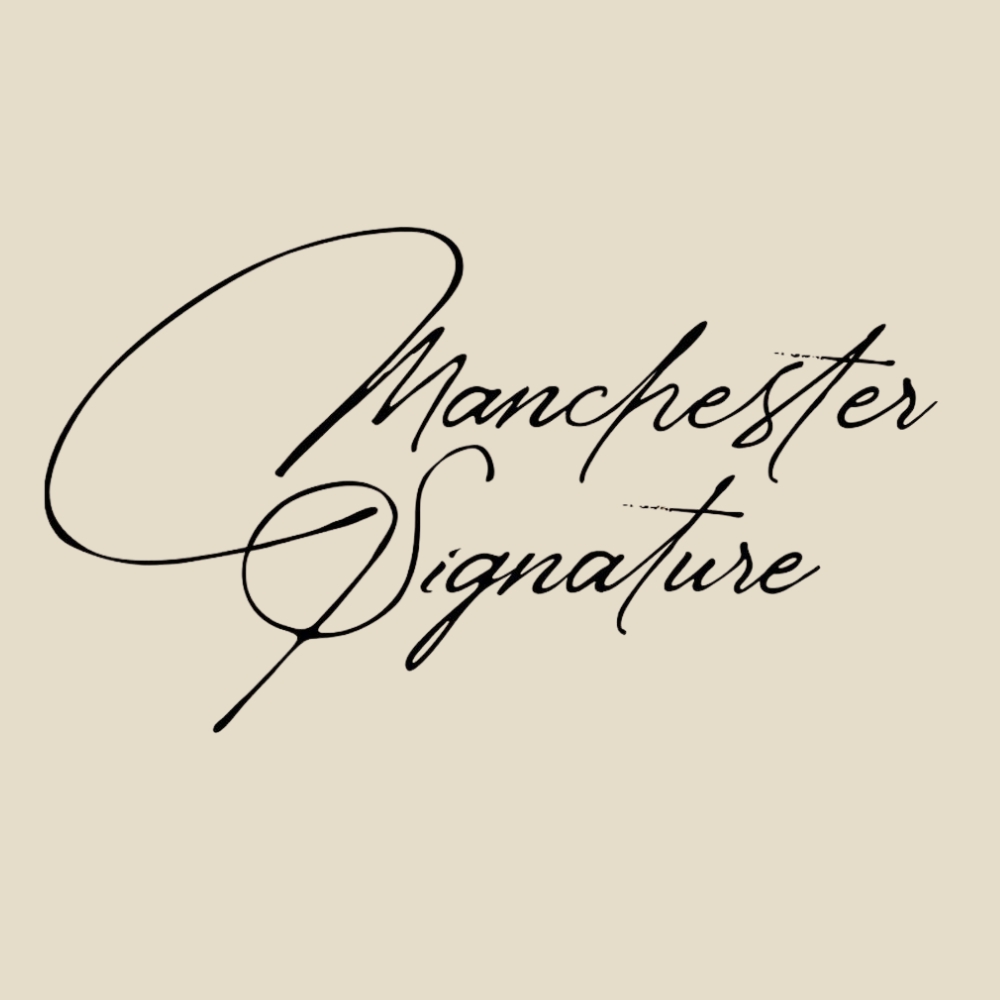
Font Việt hóa Wellyon
Font Việt hóa Wellyon mang phong cách hiện đại với các nét chữ bay bổng, mềm mại và có độ tự nhiên cao như chữ viết tay thật. Font vừa đảm bảo tính thẩm mỹ, vừa dễ đọc, phù hợp với các thiết kế logo cá nhân, thiệp mời, chữ ký email hoặc các sản phẩm sáng tạo mang tính nghệ thuật.
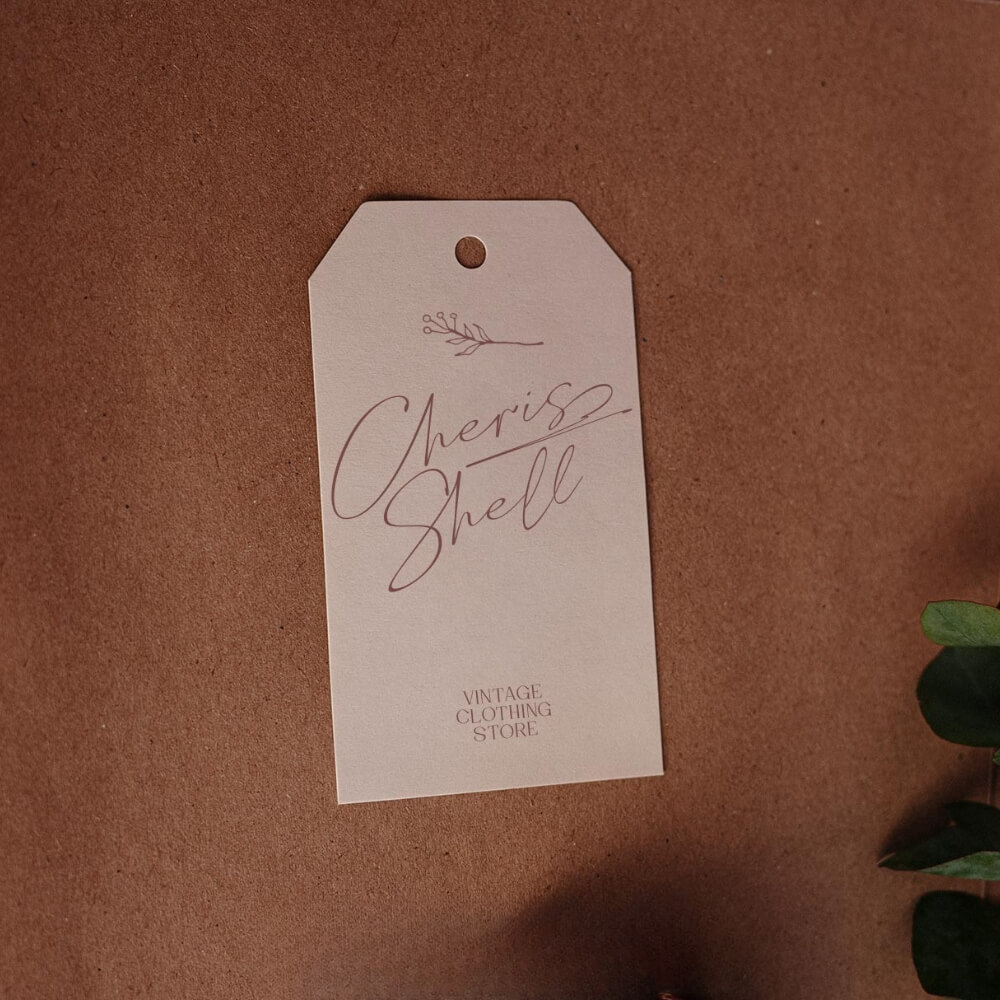
Font Việt hóa Omaha Beach
Font Việt hóa Omaha Beach nổi bật với phong cách mạnh mẽ, phóng khoáng. Các nét chữ dày, uốn lượn rõ ràng giúp tạo điểm nhấn thị giác tốt, rất thích hợp cho poster, banner, logo thời trang hoặc các thiết kế cần sự cá tính và ấn tượng mạnh.
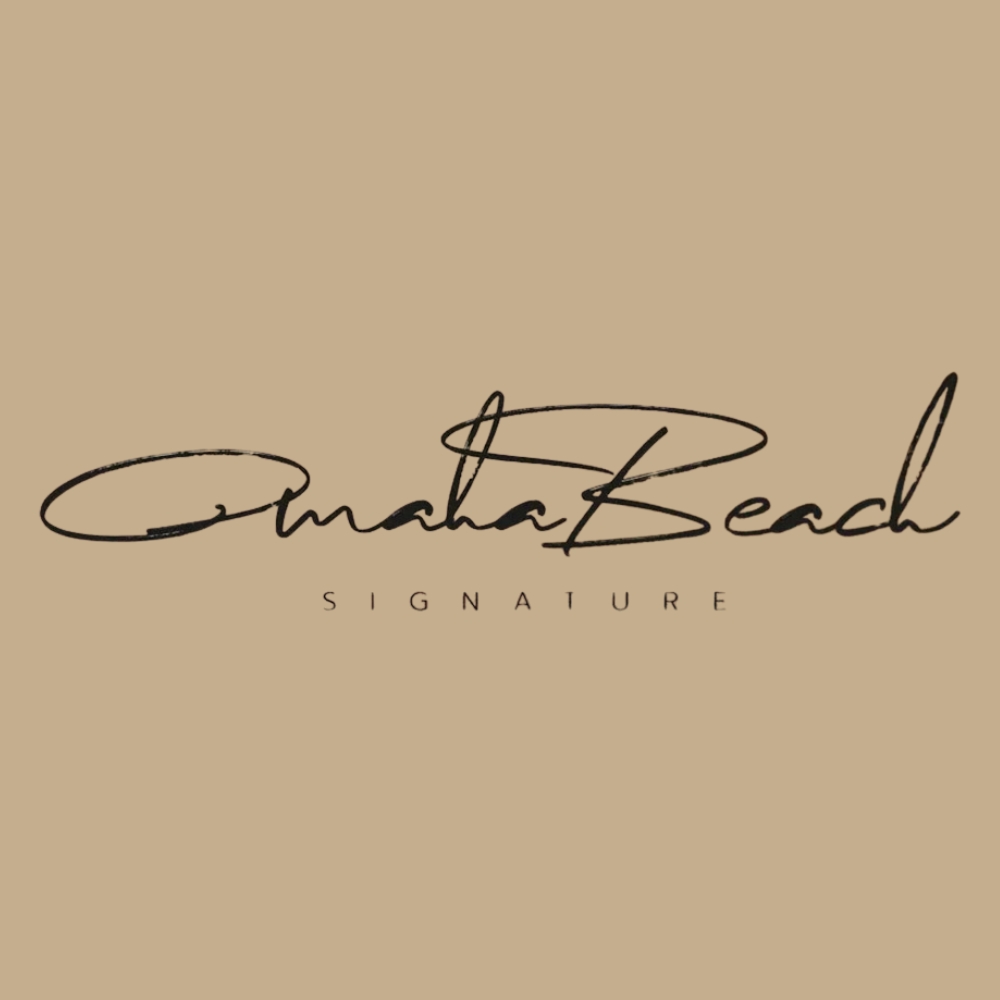
Font Việt hóa Frenchasette
Font Việt hóa Frenchasette có nét chữ thanh mảnh, mềm mại và giàu cảm xúc. Phong cách nhẹ nhàng, tinh tế giúp font trở thành lựa chọn phù hợp cho thiệp mời, logo cá nhân, thiết kế thời trang hoặc các ấn phẩm nghệ thuật cao cấp.
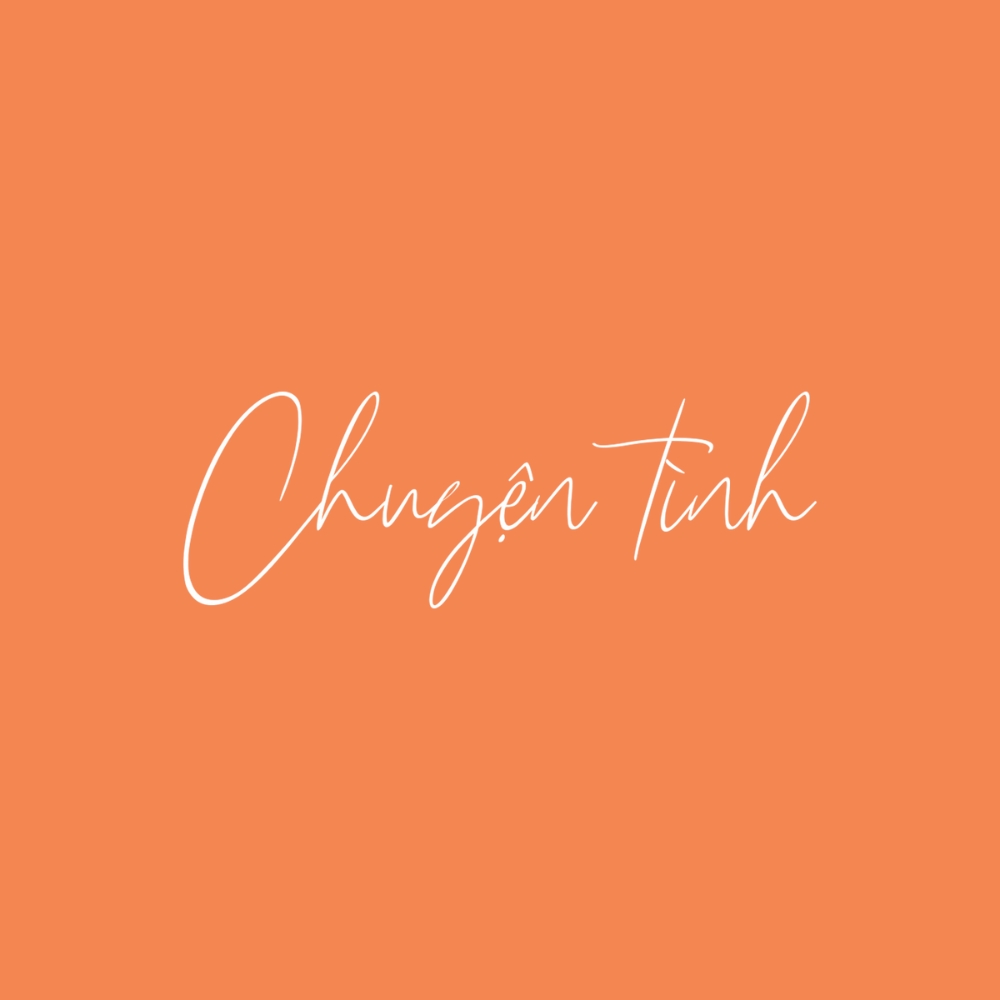
Font Việt hóa TQ Kingston
Font Việt hóa TQ Kingston mang phong cách hiện đại, uyển chuyển với độ cân đối cao. Font giúp thiết kế trở nên tinh tế và chuyên nghiệp hơn, thường được sử dụng trong logo thương hiệu, tiêu đề poster hoặc chữ ký cá nhân.
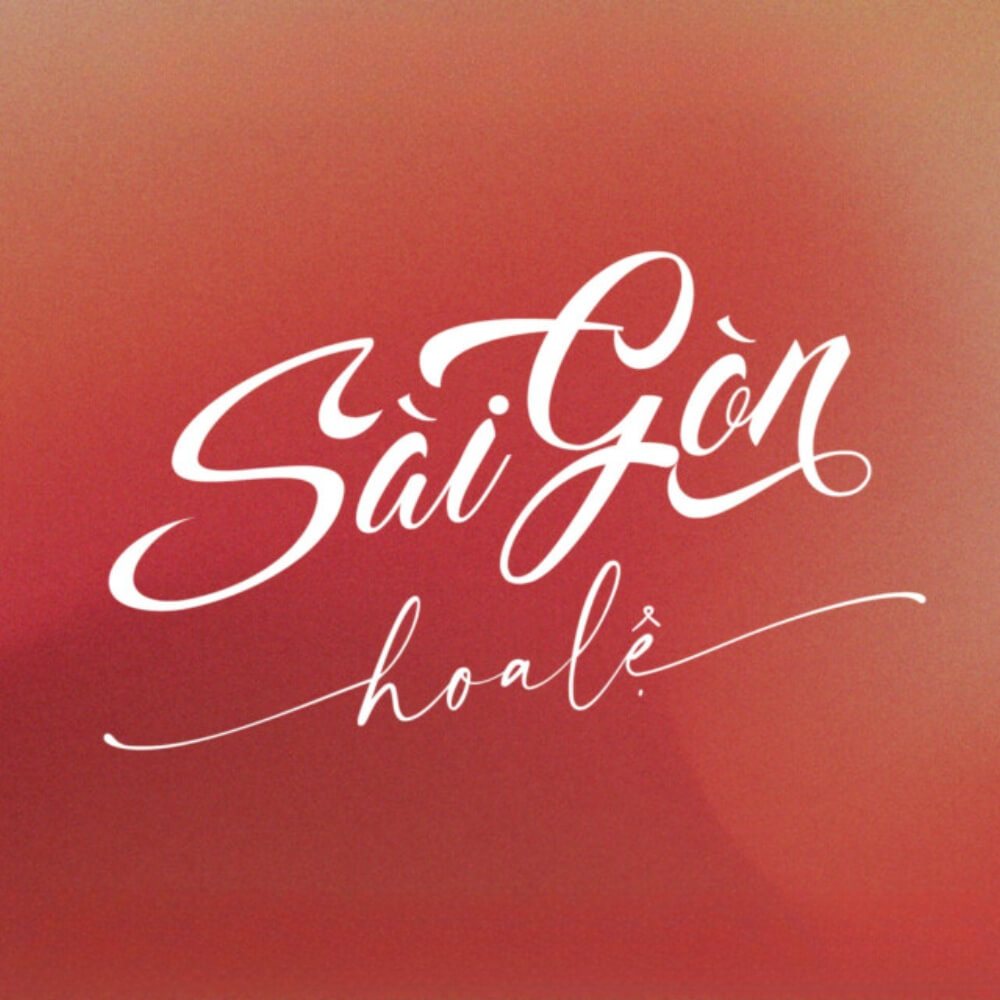
Font Việt hóa SVN Hamstring
Font Việt hóa SVN Hamstring sở hữu các nét chữ mềm mại, bay bổng, tạo cảm giác thanh thoát và nhẹ nhàng. Font phù hợp với các thiết kế thiệp cưới, logo, bao bì sản phẩm hoặc những dự án mang phong cách lãng mạn, tinh tế.
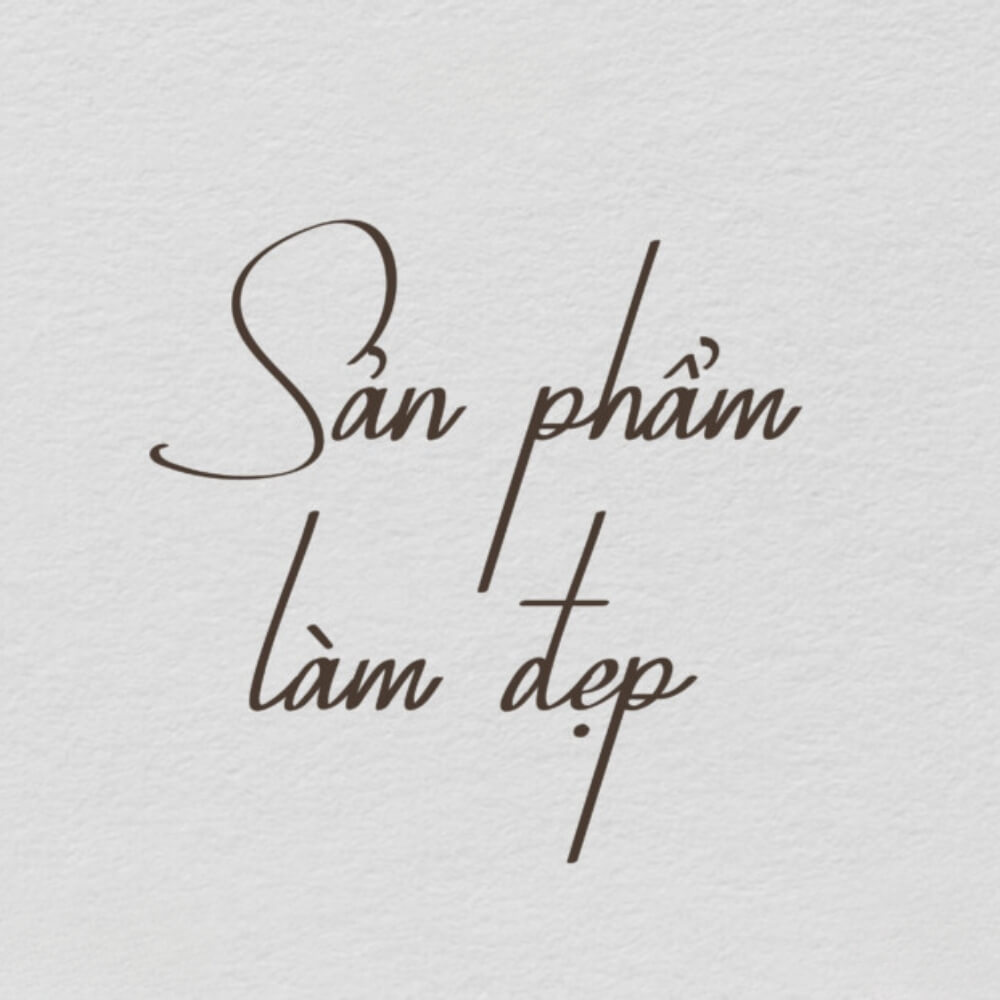
Font Việt hóa SVN Housttely Signature
Font Việt hóa SVN Housttely Signature mang phong cách hiện đại với các đường nét uyển chuyển và có tính cá nhân hóa cao. Font giúp các thiết kế logo, chữ ký hoặc ấn phẩm thương hiệu trở nên độc đáo và mang dấu ấn riêng biệt.
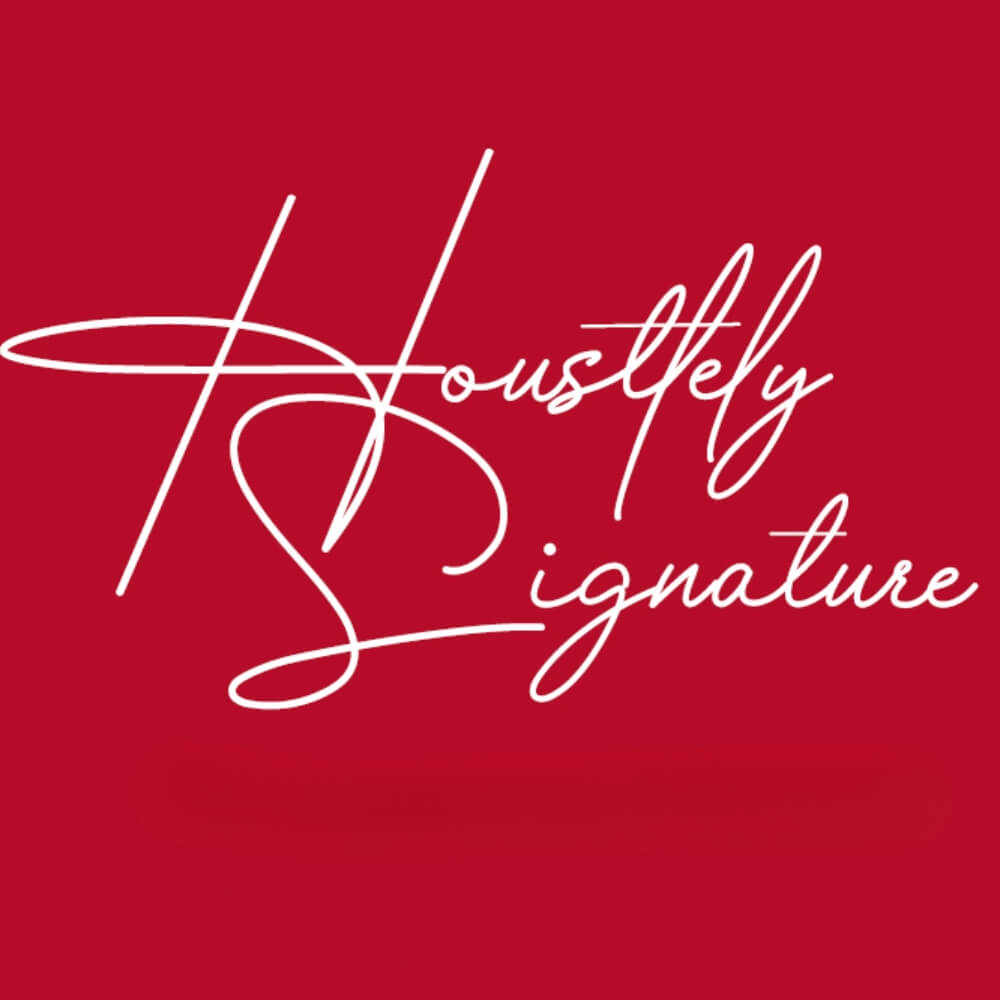
Font Việt hóa SVN Diamonda
Font Việt hóa SVN Diamonda nổi bật với vẻ đẹp sang trọng và tinh tế. Các nét chữ mềm mại, cân đối giúp font phù hợp cho logo cao cấp, bao bì sản phẩm hoặc các thiết kế cần thể hiện sự chuyên nghiệp và đẳng cấp.
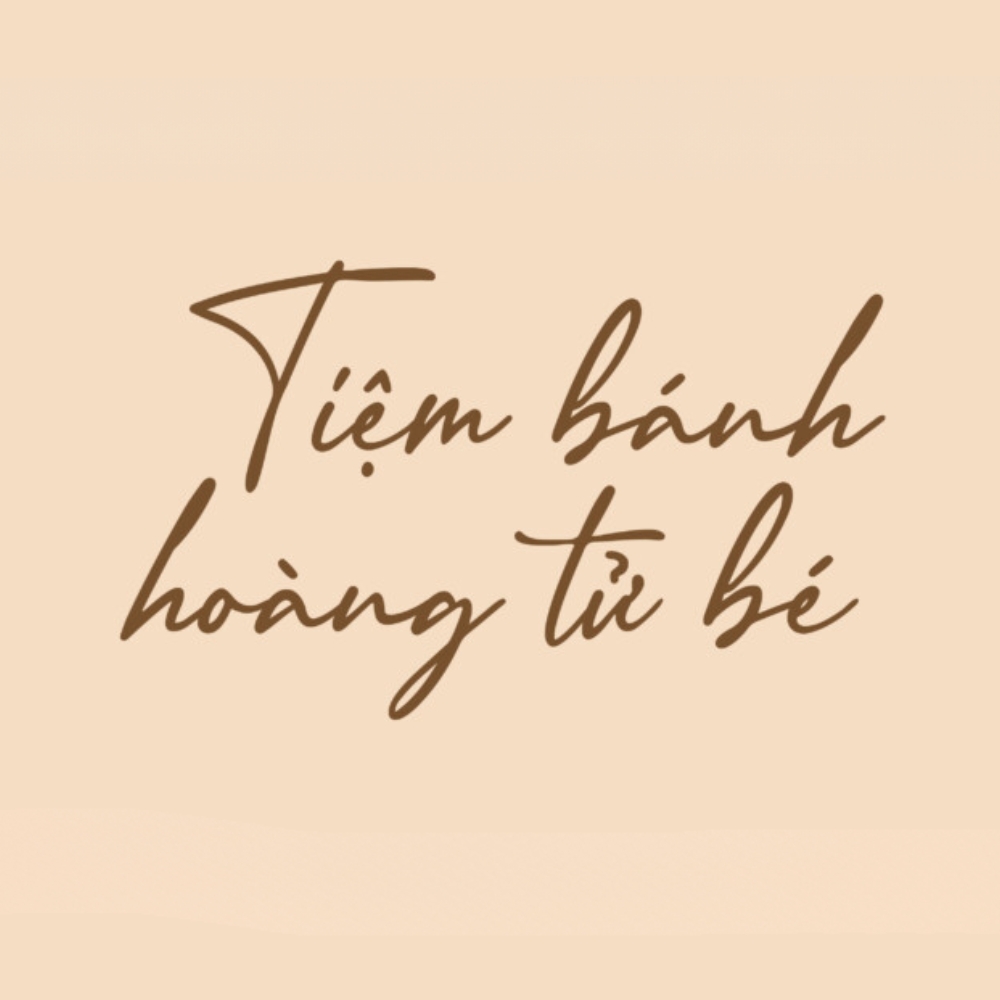
Font Việt hóa SVN Austin
Font Việt hóa SVN Austin mang phong cách thanh lịch với đường nét uyển chuyển và hài hòa. Font phù hợp cho các thiết kế hiện đại như logo thương hiệu, thiệp mời, poster hoặc bìa sách, giúp tăng tính thẩm mỹ và độ nhận diện.
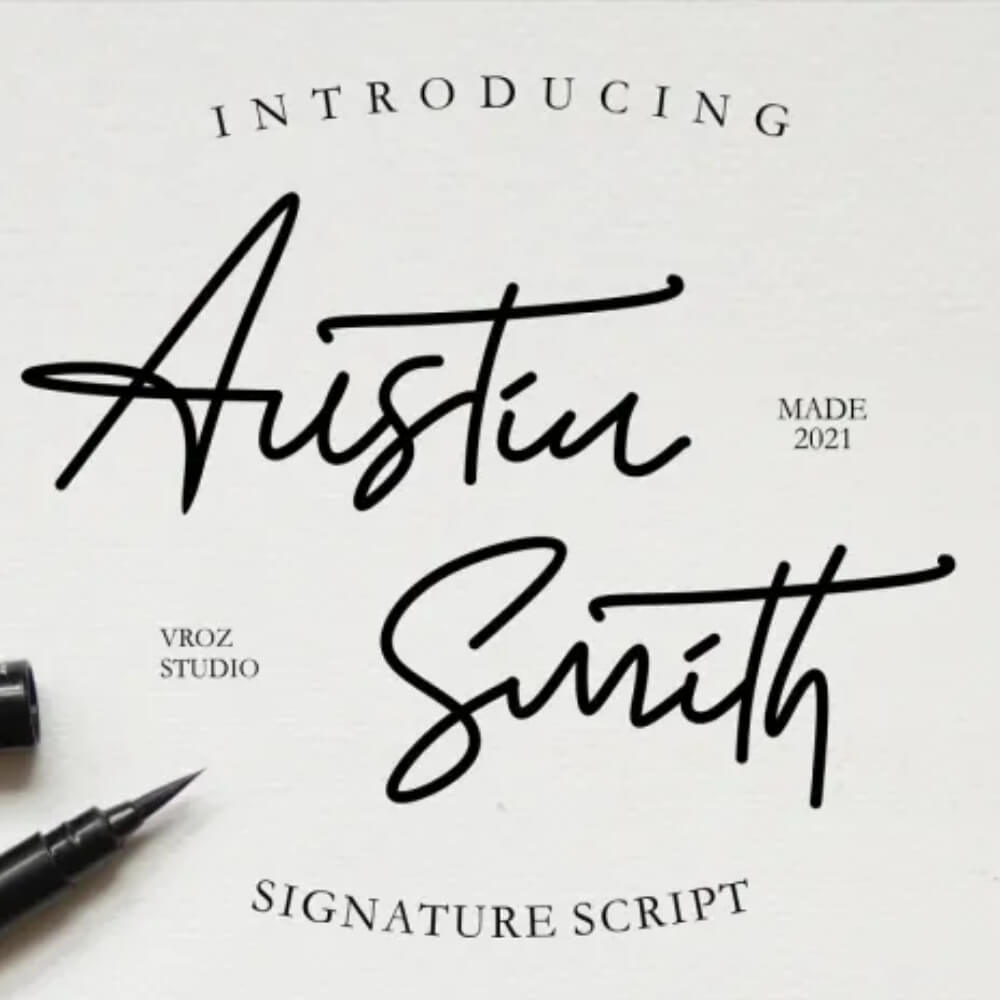
Font Việt hóa SVN Janelotus
Font Việt hóa SVN Janelotus có nét chữ mảnh, bay bổng và giàu tính thẩm mỹ. Font giúp thiết kế trở nên nhẹ nhàng, tinh tế và mang tính cá nhân hóa cao, phù hợp với logo, thiệp cưới, portfolio hoặc các sản phẩm sáng tạo.
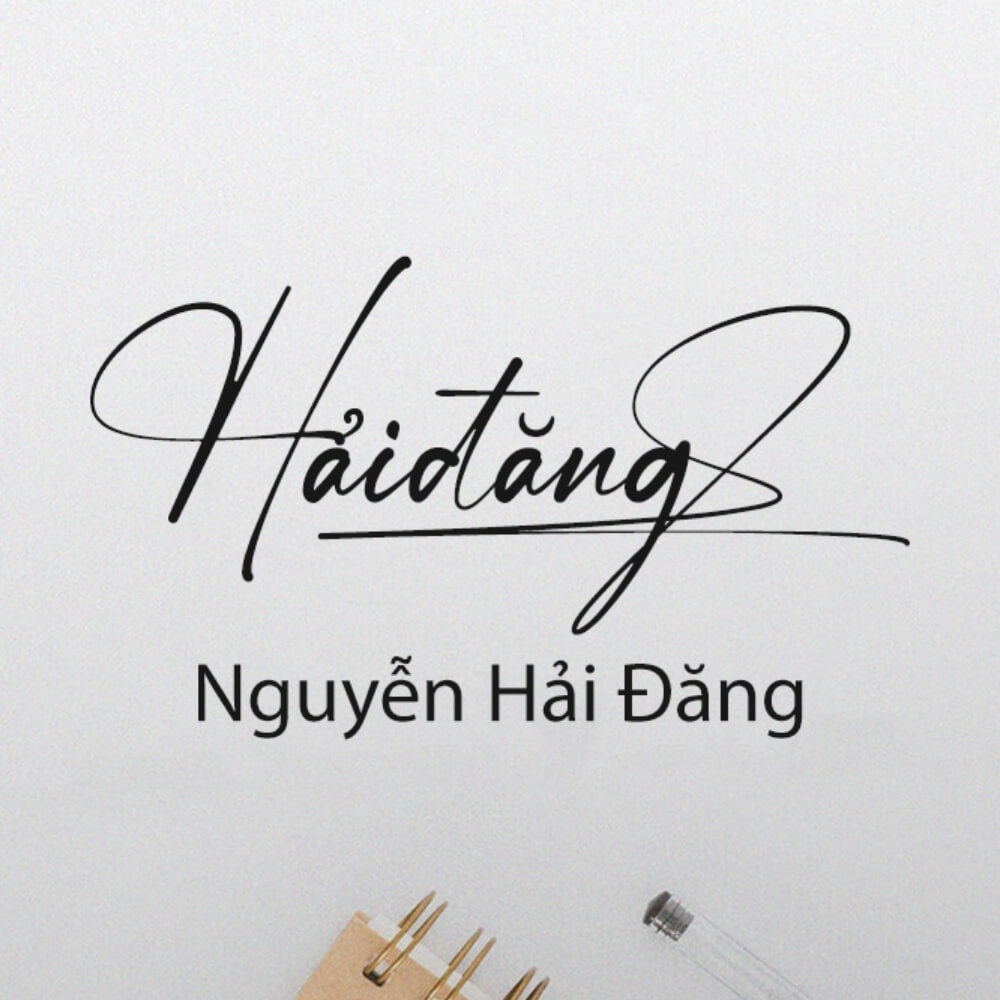
Font Việt hóa NVN Motherland Signature
Font Việt hóa NVN Motherland Signature mang phong cách viết tay mềm mại, tự nhiên và gần gũi. Font phù hợp cho logo thương hiệu, thiệp cưới, bìa sách hoặc các thiết kế cần thể hiện dấu ấn cá nhân rõ rệt.
Font Việt hóa Shelia
Font Việt hóa Shelia có nét chữ nhẹ nhàng, uyển chuyển, tạo cảm giác thân thiện và dễ tiếp cận. Đây là lựa chọn phù hợp cho logo cá nhân, thiệp mời, bao bì sản phẩm hoặc chữ ký email.
Font Việt hóa SVN Rustling Sound
Font Việt hóa SVN Rustling Sound mang phong cách cá tính với nét chữ đậm, rõ ràng và có độ tương phản cao. Font rất phù hợp cho poster, tiêu đề hoặc logo thời trang cần tạo điểm nhấn mạnh mẽ và thu hút.
Font Việt hóa 1FTV Photograph Signature
Font Việt hóa 1FTV Photograph Signature mang phong cách sáng tạo, bay bổng và giàu tính nghệ thuật. Font phù hợp cho các thiết kế logo cá nhân, thiệp mời, poster hoặc bìa sách, giúp thể hiện rõ nét cá tính riêng của từng dự án.
Font chữ ký Việt hóa là lựa chọn hoàn hảo để tạo nên những thiết kế tinh tế, chuyên nghiệp và mang dấu ấn riêng. Việc chọn đúng font không chỉ giúp tăng tính thẩm mỹ mà còn góp phần nâng cao hình ảnh thương hiệu.